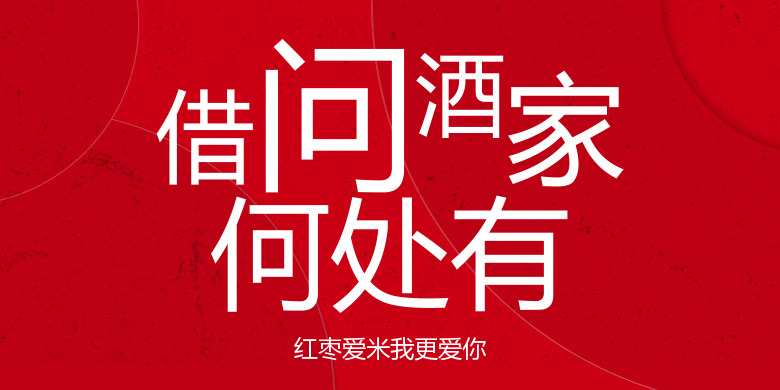
红枣爱米我更爱你
红枣爱米我更爱你,这款字体结构工整、笔画清晰,兼顾美观与易读性,适用于标题、正文、海报、包装、LOGO 等多种场景。字形优雅稳定,风格百搭耐看,适配日常排版与创意设计,让文字呈现更舒适、更具质感。红枣爱米我更爱你一笔一画,皆是细节,以均衡的比例、流畅的线条打造舒适视觉体验,字形端正大气,风格简约现代。无论是商业设计、品牌宣传还是日常排版,都能轻松驾驭,让文字更有格调与力量。红枣爱米我更爱你字体下载。